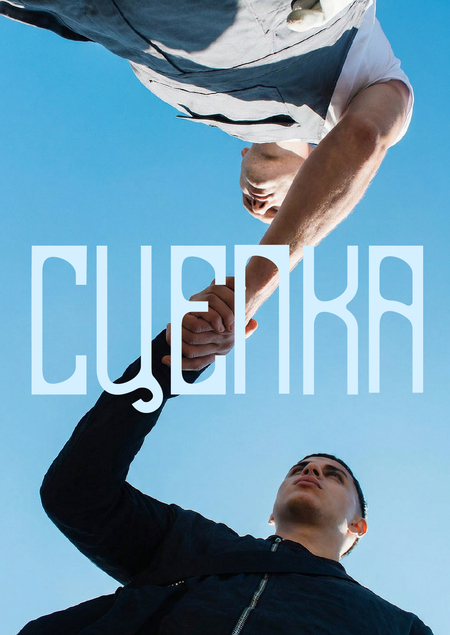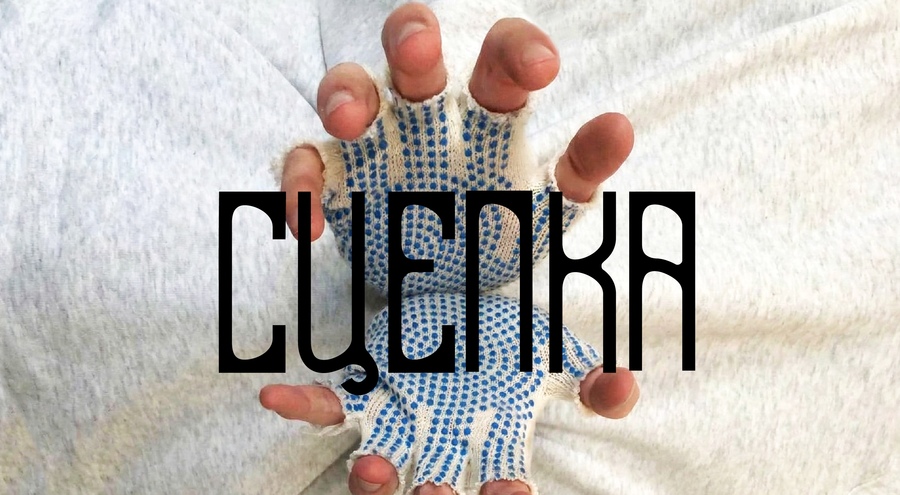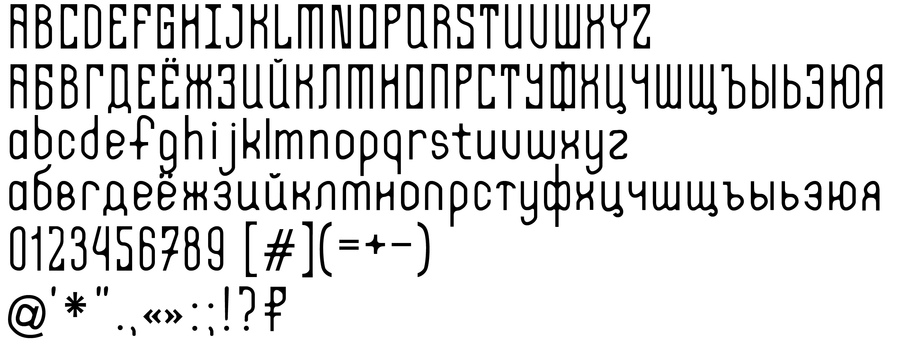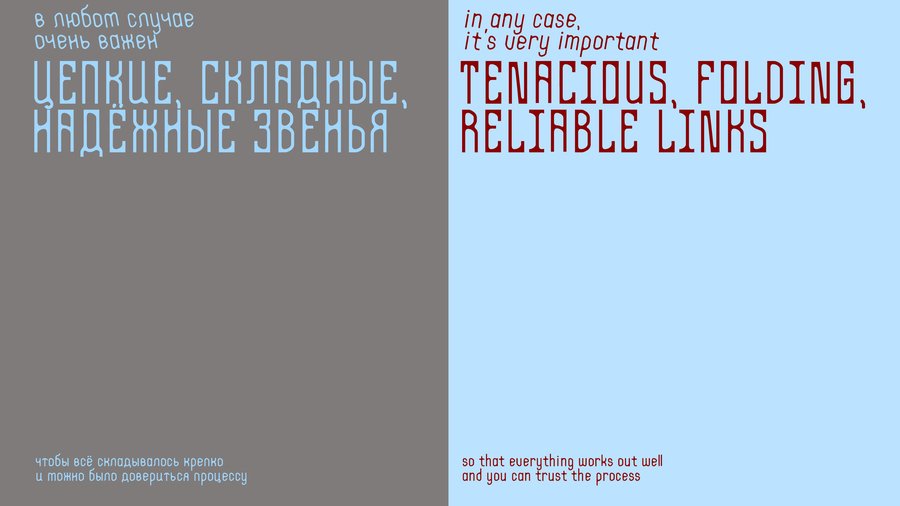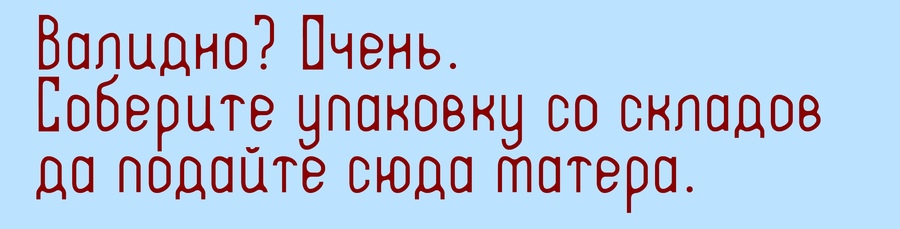
шрифт СЦЕПКА
Концепция
задача: построить на шрифте айдентику для центра, объединяющего художников и ремесленников идея: создать шрифт способный встать между двух разноплановых категорий, создающий ощущение цельной, крепкой, но неоднозначной цепи. Соединить в нём стык и пластику, функцию и декорирование, модульность и аналоговость.
реализация: Вытяннутый гротеск, в основе которого лежит трапецевидная форма, отсылающая к утилитарным инструментам. Добавить нюанс, создающий небольшой, но цепкий контраст.